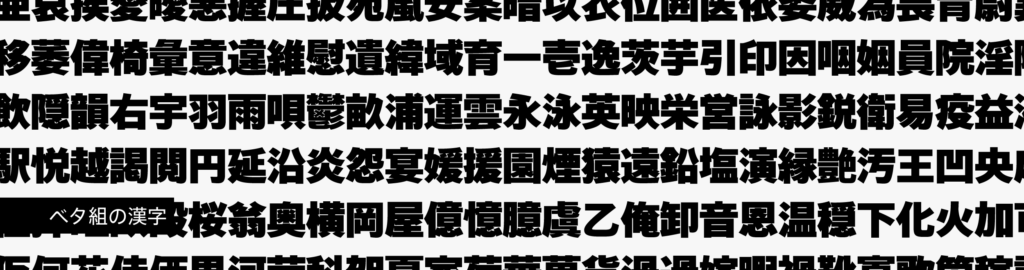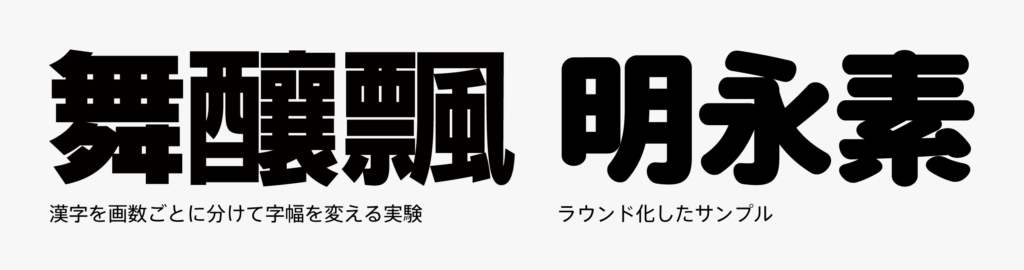
TPスカイ モダン Blk 開発ストーリー 03「実験!」
このシリーズの前回の記事で「漢字の試作で骨格や太さの調整をした」という話を紹介しましたが、試作段階では他にもさまざまな調整や実験がありました。例えば、字面率を数パーセント毎に刻んだサンプルです。最終的にはギリギリまで大きめの字面率を採用したので、モダンBlkをベタ組にすると文字と文字の間が狭くみっちり並びます。
他にも太さを意識した実験として、平体をかけたサンプルを作ってみたり、漢字を画数ごとに分けて字幅を変える実験もしていました。TPスカイにはラウンドファミリーがあるので、モダン Blkもラウンド化したサンプルを作りました。特に試作段階はリリースする製品に直接反映されない寄り道も多いですが、様々なアイデアを試せる楽しい時間でもあります。